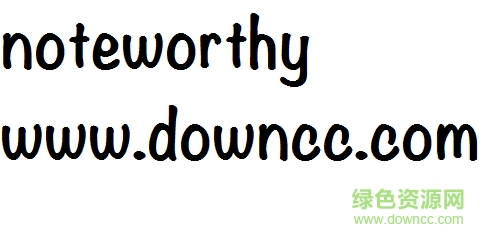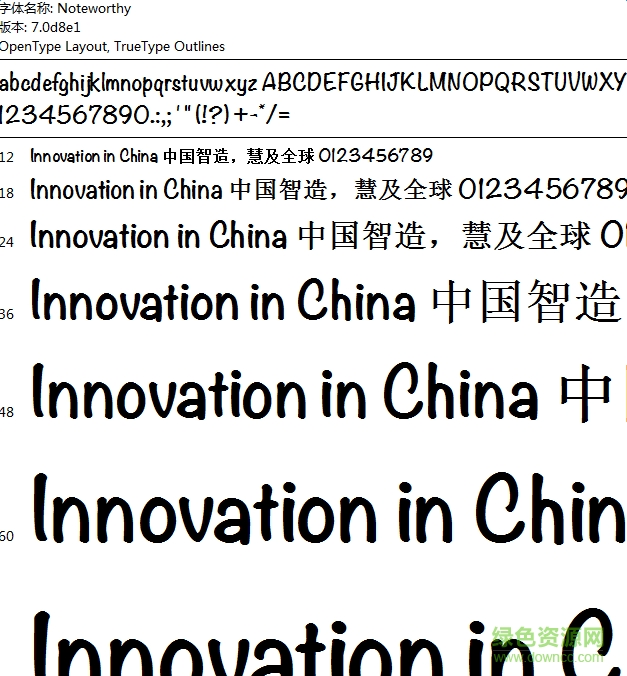
noteworthy字體是一款英文字體軟件,此字體為手寫字體,十分有創(chuàng)意,可用于海報漫畫設(shè)計應(yīng)用,整體效果十分灑脫,喜歡的朋友歡迎到綠色資源網(wǎng)下載體驗(yàn)!
noteworthy字體筆畫不拘一格,給人清新脫俗的感覺,十分好看迷人,綠色資源網(wǎng)為您提供綠色免費(fèi)的noteworthy字體下載!